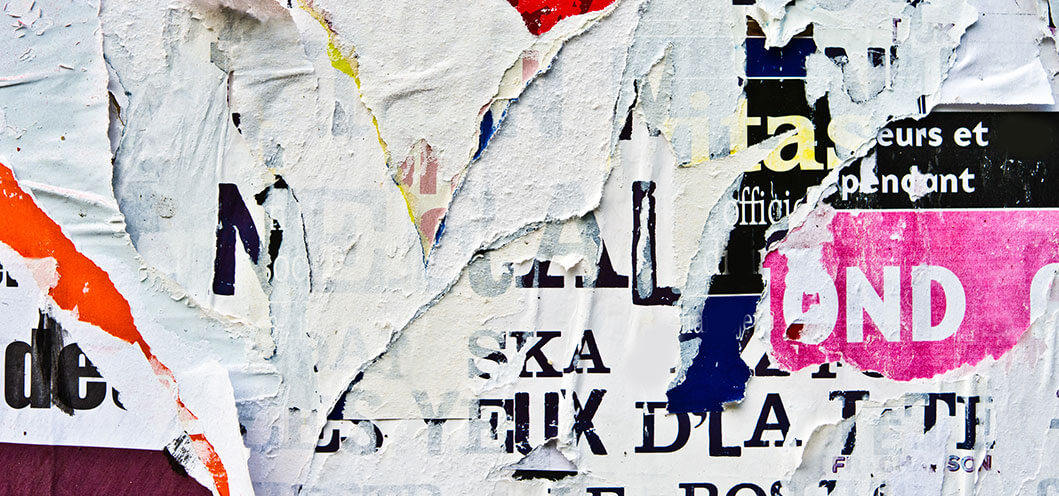
TIPOLOGIA OU TIPOGRAFIA, EIS A QUESTÃO
Todos os dias nos deparamos com designers falando: "Escolhi a tipologia Garamond Bold para os títulos desse trabalho" ou "Para esse trabalho acho que o ideal é a tipografia Gotham Regular". Mas qual é o termo certo (ou são sinônimos?) e o que significa falar em tipologia ou tipografia? Escrevemos esse artigo bem curtinho para responder a essa pergunta.
Tipologia é um termo que constantemente é banalizado em textos, tipologia é o estudo que resulta na caracterização de qualquer elemento, seja ele uma fonte, um ser vivo ou qualquer outra realidade que precise ser caracterizada. Esse termo que muitos acreditam ter total relacionamento com as fontes, é muito usado na arquitetura, na biologia, entre outros. Pode-se entender que tipologia é um sinônimo para classe, família, gênero, enfim uma classificação generalista de algo ou alguma coisa.
No dicionário Michaelis: ti.po.lo.gi.a (tipo+logo+ia¹) sf 1 Caracterização dos tipos humanos, dos seres vivos ou de realidades quaisquer considerados num estudo. 2 Descrição geral desses tipos em cada caso. 3 Por abreviação, V biotipologia.
Tipografia é uma palavra originada do grego typos (impressão) + graphé (escrita). O termo tipografia surgiu para falar da arte da composição e impressão com tipos móveis, porém com o passar dos anos passou a referir-se a composição de textos que formam um projeto gráfico.
No dicionário Michaelis: ti.po.gra.fia (tipo+grafo+ia) sf 1 Arte de compor e imprimir com tipos. 2 Estabelecimento onde essa arte é praticada. 3 tip A seção da oficina onde se realiza o trabalho de composição. 4 gír Exploração disfarçada do lenocínio.
Sendo assim, pode-se concluir que tipologia, nesse caso, é a classificação dada a um conjunto de tipos (uma família de fontes ou classificação de fontes) e tipografia é o tipo escolhido ou desenhado para ser utilizado em um determinado projeto gráfico.